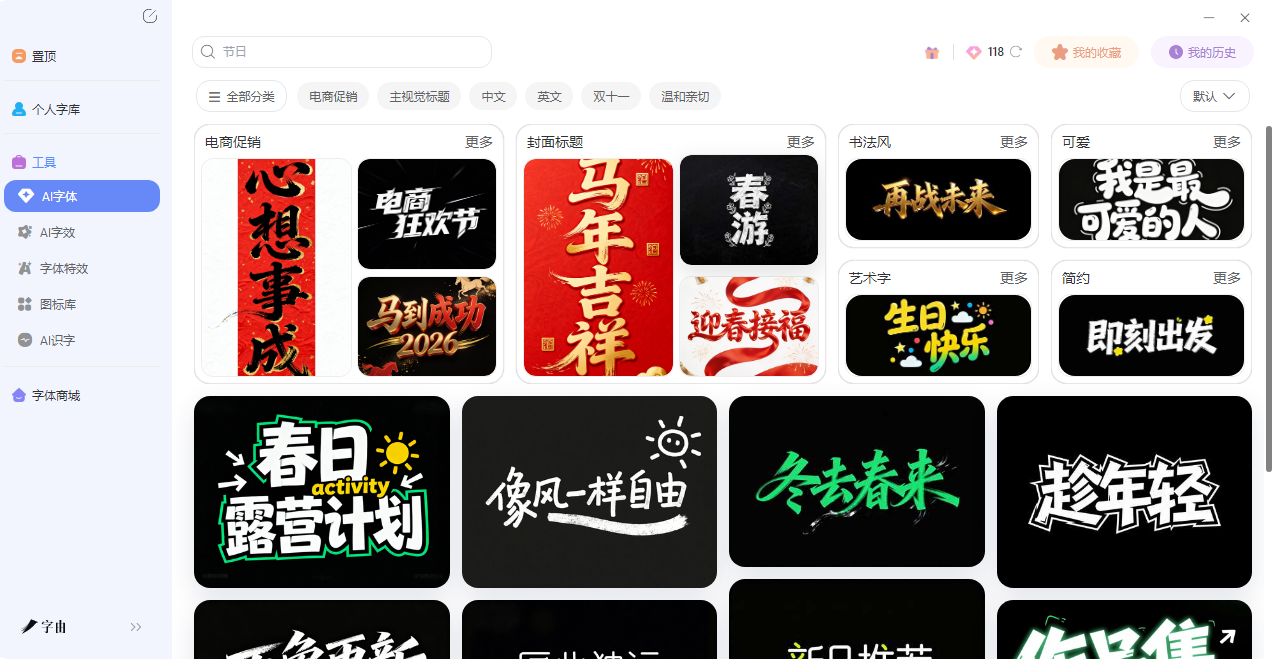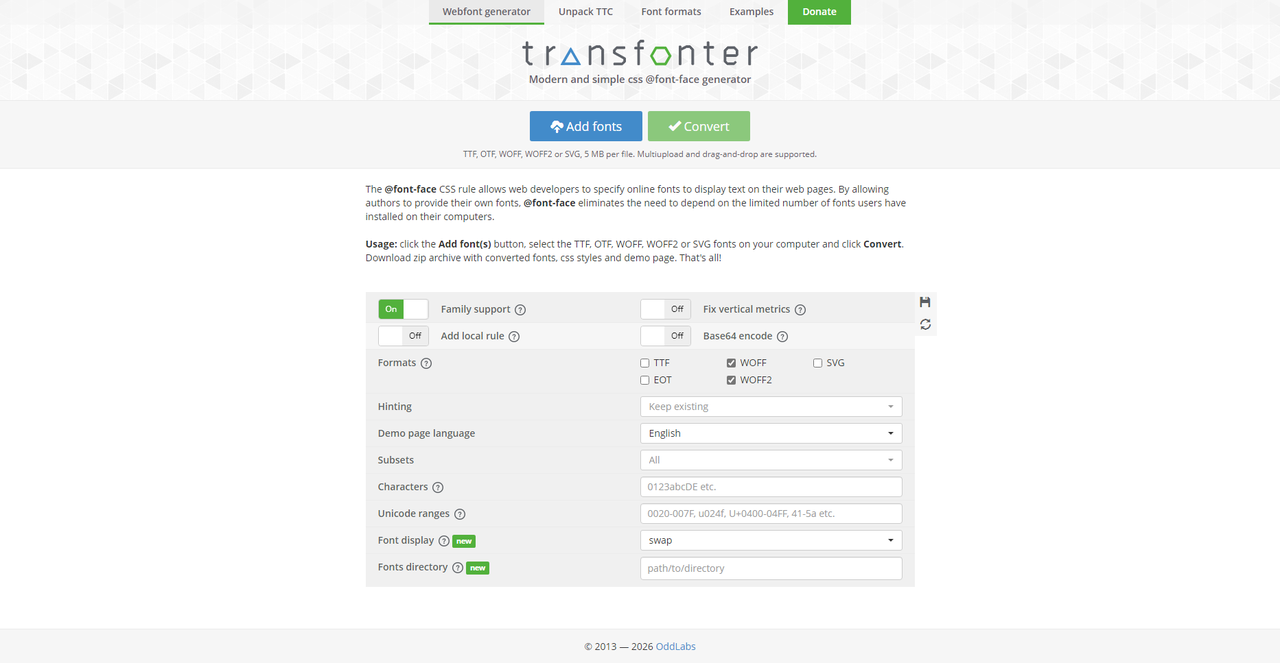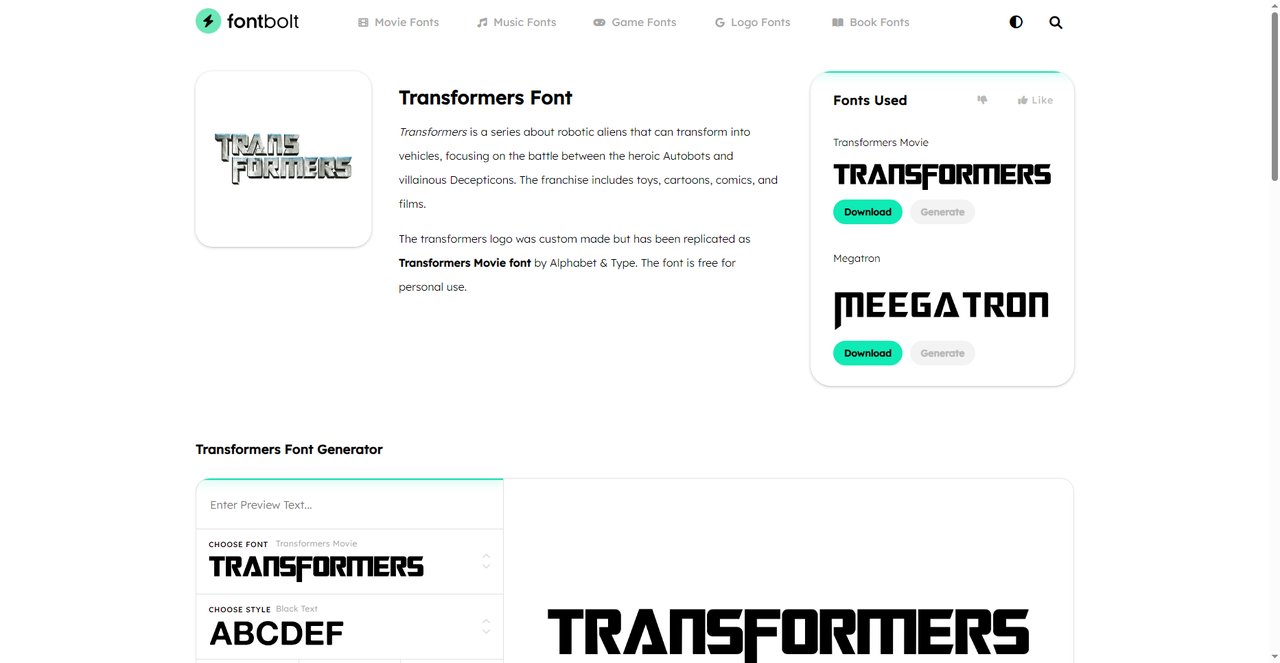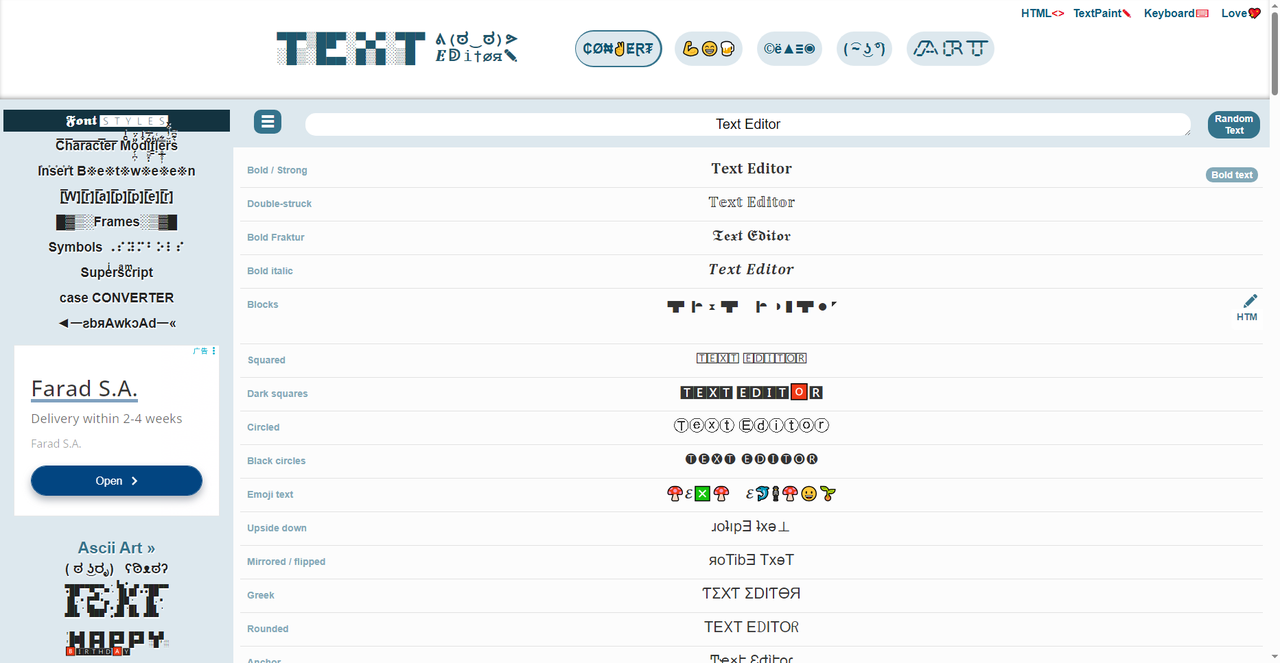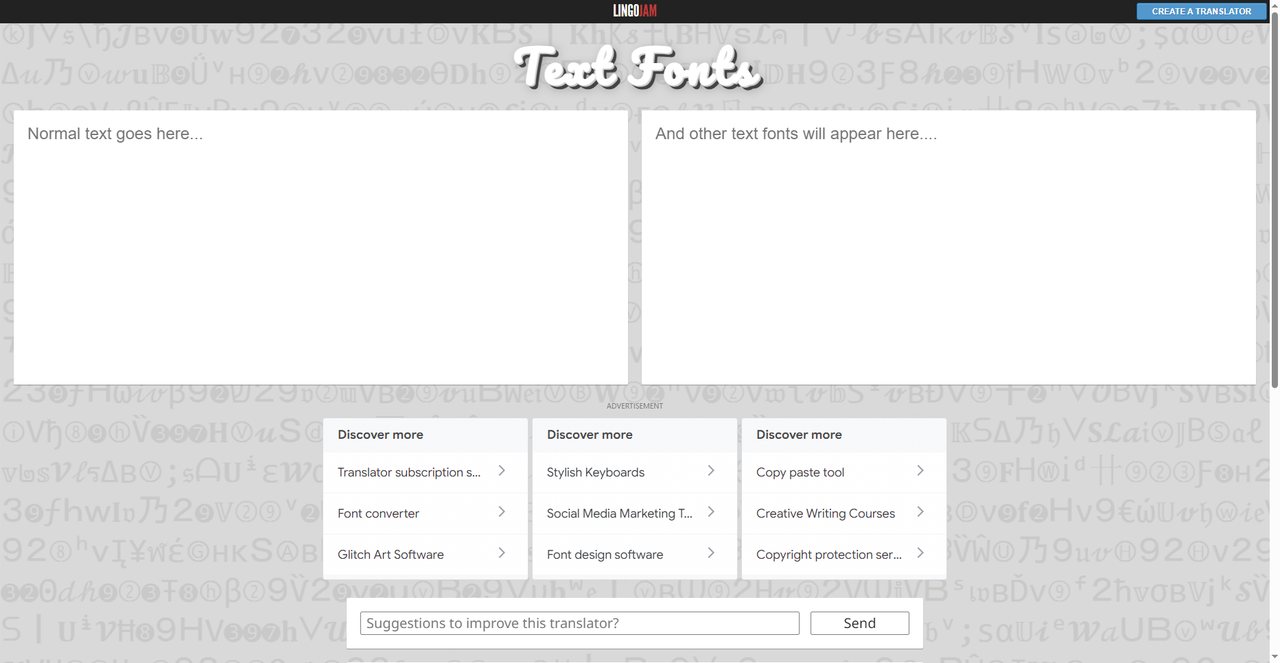
不用下载软件,文字转换器在线生成
如果当你觉得设计画面当中的字体不太合适的时候,肯定想着会换下一款,但是传统下载字体的方法是在是太麻烦;又或者是你在写文章的时候想换其他字体看看效果,但是下载那么多过来一起试又太浪费时间,今天一个办法就可以解决:那就是用文字转换器。输入文字就能在线生成各种样式的字体效果,一键复制粘贴就能用。今天我就天整理了5个不同方向的文字转换工具,有专门帮设计师一键换字体的,有做网页字体格式转换的,有生成变形金刚风格艺术字的,也有专门做Unicode 花体字和特效文本的。不管你是设计师、开发者,还是只是想发一条不一样的朋友圈,这里总有一款适合你。
先来介绍字由,打开字由的网页版以后,里面收录了上万款字体,按黑体、宋体、楷体、书法体、手写体等风格分类,也可以按“免费商用”筛选。在PS或AI里选中文字图层,回到字由客户端点击想要的字体,文字会实时切换成对应的字体效果,不需要下载安装包,不需要打开系统字体文件夹。字由支持的设计软件包括Photoshop、Illustrator、InDesign、Figma、Sketch、CorelDRAW等,日常设计基本全覆盖。
它的“文字转换”逻辑和普通在线工具不太一样——不是生成Unicode字符,而是让你从字体库里选一款字体,然后一键应用到你正在用的设计软件里。
除了字体库一键切换,字由还有AI字体功能。打开客户端顶部的“AI工具”,里面有400多种字体特效模板,按国潮风、手写书法、科技感、霓虹灯等风格分类。选一个模板,输入自己的文案,点一下生成,10秒左右就能拿到一张带特效的艺术字图片,可以直接下载PNG格式用在海报或封面上。
2、Transfonter
第二个工具叫Transfonter,一个在线字体格式转换器,专门给网页开发者用的。做网站的时候,设计师给的字体文件可能是.ttf或.otf格式,但这些格式在不同浏览器上的兼容性不一样,直接引用可能显示不正常。Transfonter的作用就是把本地字体文件转换成网页可用的多种格式,比如WOFF、WOFF2、EOT、SVG,同时自动生成对应的@font-face CSS代码,开发者把代码复制到样式表里,字体就能在网页上正常显示了。
使用方式很简单:上传一个字体文件(TTF、OTF、WOFF、WOFF2或SVG,单文件不超过5MB),勾选需要的输出格式,点“Convert”按钮,下载一个压缩包,里面包含转换后的字体文件、CSS样式和演示页面-。界面里还有一些高级选项,比如Base64编码、字符子集、Unicode范围设置等,有经验的开发者可以根据项目需要做精细化配置。这个工具适合前端开发者和网页设计师,属于“专业型”文字转换器,和普通用户日常用的花体字生成器不是一回事。
3、FontBolt Transformers Font Generator
第三个工具是FontBolt旗下的Transformers Font Generator,一个专门生成艺术影风格标题的艺术字生成。
网站还提供了系列相关字体的直接下载选项,比如基于电影Logo复刻的免费字体,支持个人使用。如果你想快速做一张变形金刚风格的标题图,或者给视频封面配个有冲击力的标题,不用打开PS慢慢调金属质感和描边,这个工具几秒钟就能出效果。FontBolt这类工具的价值在于“特定风格一键生成”,和通用型花体字生成器不同,它针对的是有明确IP风格的场景,适合游戏视频封面、粉丝创作、活动海报等用途。
4、TEXT TOOLS
第四个工具是TEXT TOOLS,一个多功能文字处理工具集合,截图里显示的核心功能是做“文字特效转换”。
它提供的玩法包括:在字母之间插入特定字符(比如把“hello”变成“h-e-l-l-o”或者“h|e|l|l|o”),给文字加边框或框架装饰,大小写快速转换(全大写、全小写、句首大写等),还有ASCII艺术生成功能——把普通文字转换成用符号拼出来的图形文字。这类工具适合做社交媒体配文、评论区高亮、个人简介装饰。想在朋友圈发一段与众不同的文字,或者在游戏昵称里加点花样,TEXT TOOLS的几个功能配合着用,效果会比纯文字丰富不少。而且它不需要注册登录,打开网页就能用,完全免费。
5、Text Fonts:Unicode
第五个工具是Text Fonts,一个典型的Unicode花体字生成器。它的工作原理是利用Unicode中的特殊字符集,把普通字母映射成样式不同的符号——比如花体、哥特体、粗体、斜体、气泡体等。用户在输入框里打字,下面会自动列出几十种不同样式的转换结果,点一下对应的样式就能一键复制。和前面几个生成图片的工具不同,Text Fonts生成的是纯文本,所以复制后可以直接粘贴到任何支持文本输入的地方——微信朋友圈、微博、抖音简介、小红书标题、游戏昵称、Discord频道名等。而且这些花体字在所有设备上都能正常显示,因为本质上它们就是Unicode标准字符,只是长得不一样。不需要接收方安装任何字体文件。